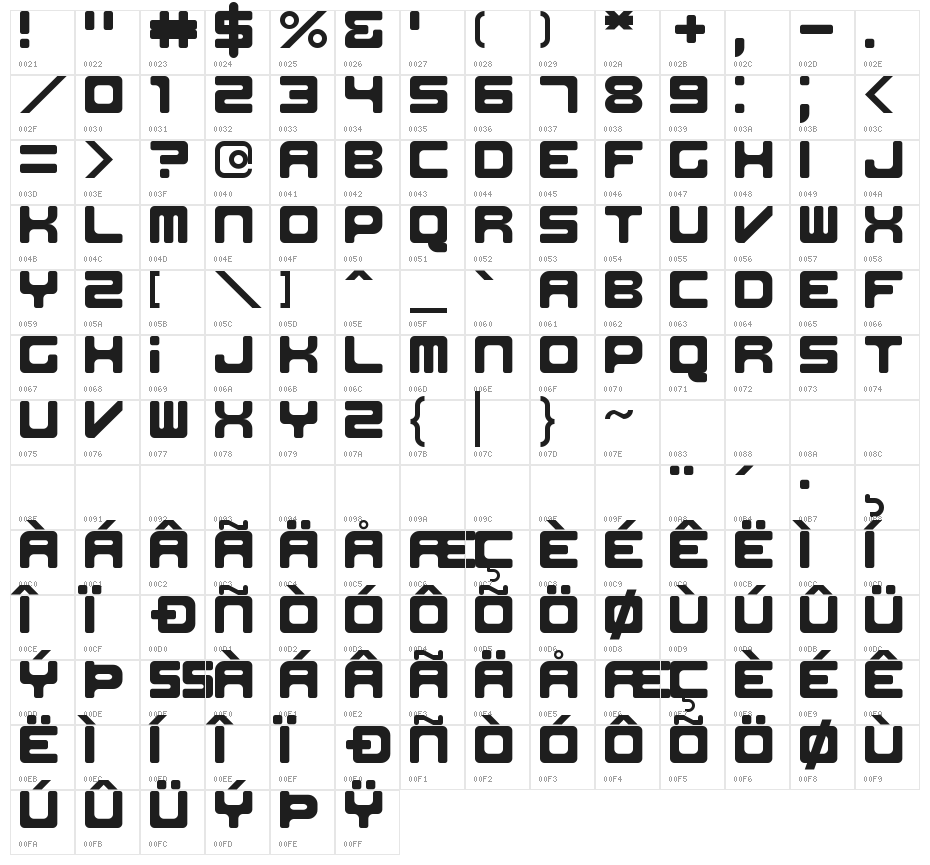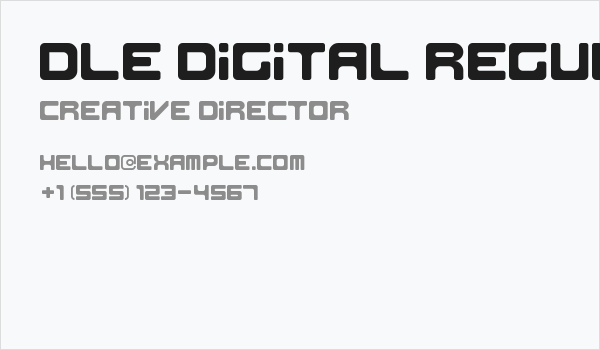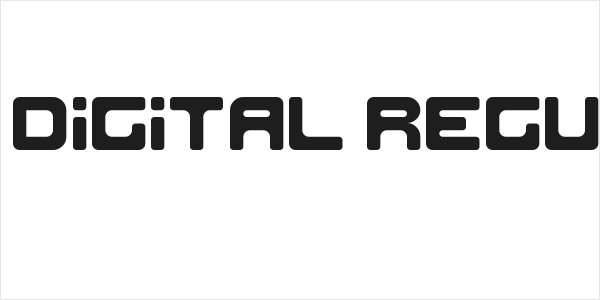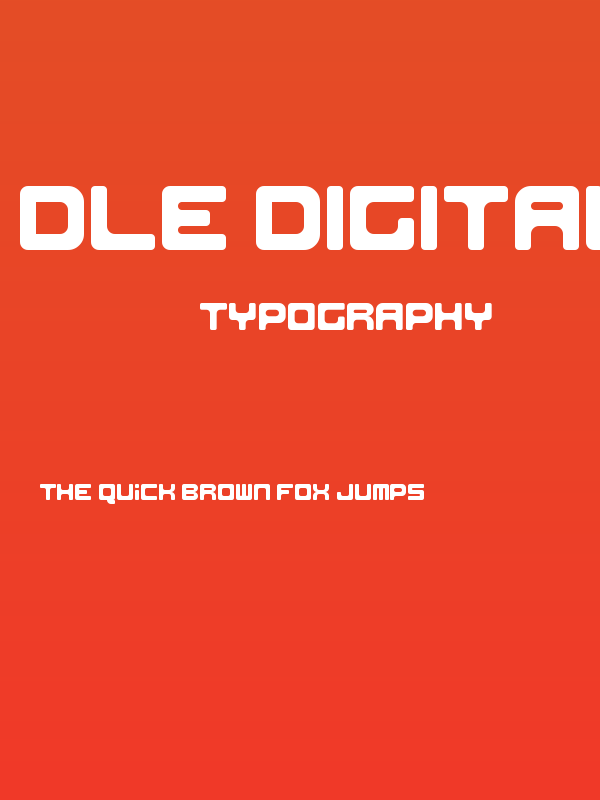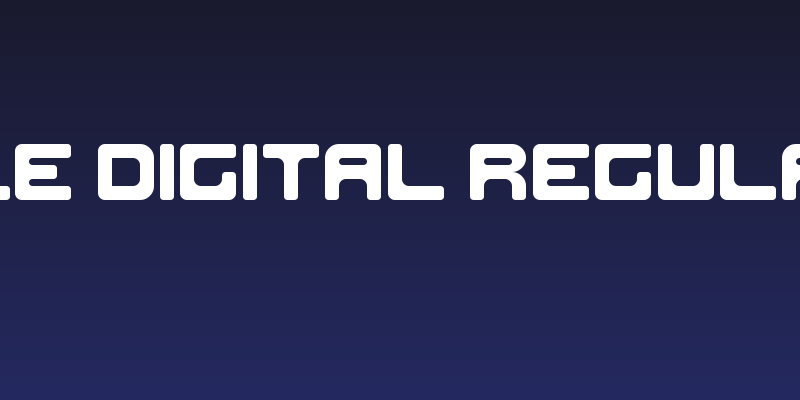
DLE Digital Regular Font
✎ Futuristic
| Категория | Futuristic |
| Область применения | Headlines, Logos, Digital interfaces |
| Рекомендуемые проекты | Ideal for tech branding, digital interfaces, video game design, and futuristic-themed posters. |
DLE Digital Regular